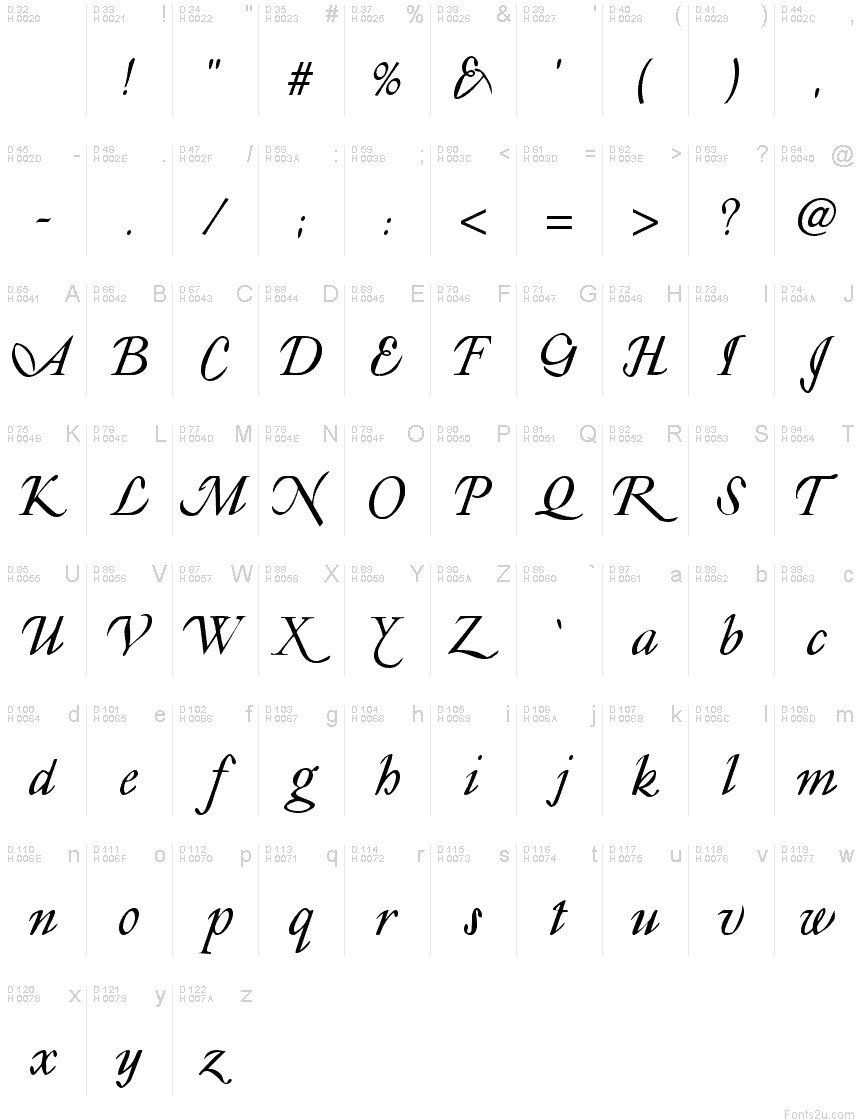
Krój pisma Lyonesse autorstwa Davida F. Nalle to darmowy font kaligraficzny z długimi, zamaszystymi pociągnięciami i formalnym, pochyłym stylem. Litery łączą się za pomocą wąskich spoiw i zakrzywionych otwarć, tworząc wyrafinowany, odręczny rytm, który sprawia wrażenie ręcznego wykonania, a nie mechanicznego procesu.
Lyonesse świetnie sprawdza się w zaproszeniach ślubnych, logotypach, papeterii, okładkach książek i kartkach okolicznościowych, ponieważ nadaje krótkim tekstom i nagłówkom pełnego wdzięku, osobistego charakteru. Ten darmowy font pasuje również do dekoracyjnych cytatów, tytułów wydarzeń i brandingu butikowego, gdy szukasz stylu script bez zbędnych zdobień.